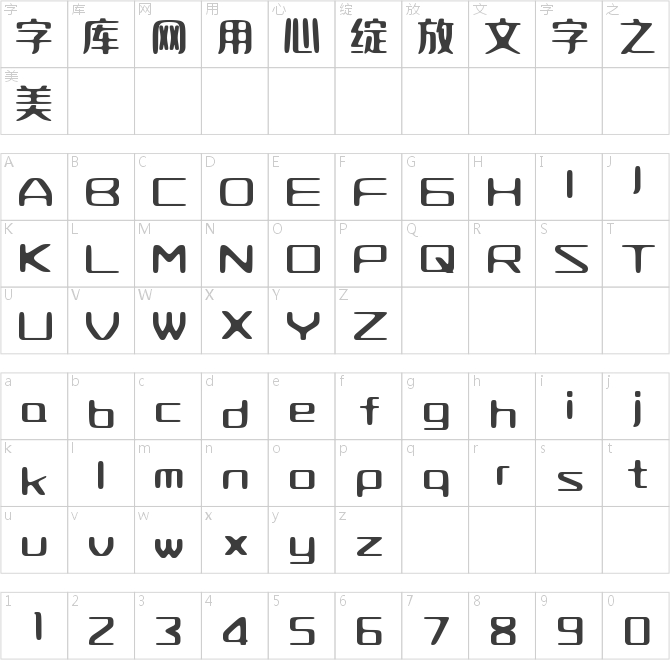
字魂229號(hào)-云瑤體是一款創(chuàng)意衍生字。字體圓潤飽滿,舒展柔和,筆畫交叉的內(nèi)側(cè)添加了圓角,彼此相融,適用于文本標(biāo)題、廣告標(biāo)語和包裝設(shè)計(jì)。
字魂229號(hào)-云瑤體字體zihun229hao-yunyaoti字庫是一款讓人賞心悅目、百看不厭的中文字體,適合各類廣告和產(chǎn)品包裝設(shè)計(jì)應(yīng)用,字體大小4.2MB,格式為ttf字體,上傳用戶是文生電腦,作者/版權(quán)方為字魂